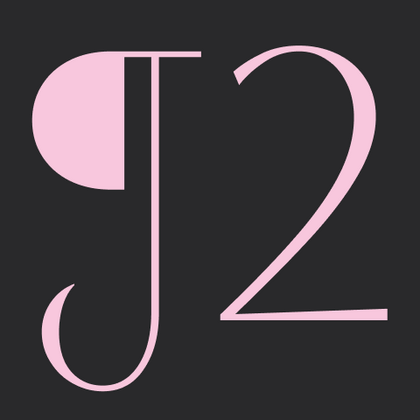
Нежные шрифты
Если требуются гарнитуры с деликатной эстетикой, где каждая линия передает легкость и изящество, отлично подойдут нежные шрифты. Их отличают плавные закругления, тонкие штрихи и воздушные пропорции, создающие ощущение тонкого вкуса. В коллекции TypeType представлены как каллиграфические варианты с рукописными нюансами, так и ультралегкие гротески — все они идеально подходят для свадебной полиграфии, косметического брендинга и женских изданий.
TT Odellia — старостильная антиква с современным рисунком, вдохновлённая венецианскими шрифтами и классической музыкой.
TT Rationalist — функциональный и оригинальный брусковый шрифт с актуальным рисунком. Он универсален и подходит как для заголовков, так и для массивов текста.
TT Jenevers стилистически относится к голландским антиквам нового стиля. В гарнитуре присутствуют характерные детали, свойственные голландским антиквам — это ассиметричная форма засечек или нерегулярный наклон овалов.
TT Quaris — изысканная и современная ленточная антиква. Перед разработкой этой гарнитуры мы провели глубокое исследование архетипов ленточных антикв.
TT Ricordi Allegria — современная ленточная антиква, отличительные особенности которой, гиперболизированная разноширинность в пропорциях, контраст между штрихами, клиновидные окончания штрихов и отсутствие традиционных засечек.
TT Modernoir — акцидентный гротеск с разноширинными пропорциями. Плавные линии и изящные формы ар-нуво в этом шрифте сочетаются с ритмичностью и импровизационной свободой джаза.
TT Ricordi Greto — неконтрастный флорентийский гротеск с динамичными пропорциями. Это единственный гротеск среди антикв в коллекции TT Ricordi, при этом в нем сохранились едва заметные засечки, отсылающие к прототипу.
TT Fellows — гуманистический гротеск с механистическими мотивами. Открытые формы, дружелюбно-нейтральный характер тонких весов и ещё более мягкий характер в жирных начертаниях.
TT Ramillas — стильная и современная антиква. Включает уникальные декоративные начертания и буквицы с цветочным орнаментом.
TT Paplane — акцидентный сквадраченный гротеск. Так, характерные черты этого гротеска — сквадраченные формы, 45-градусные срезы и обтекаемые внешние контуры.
TT Cometus — современная брусковая антиква. Название гарнитуры отсылает к образу кометы — мощного увесистого тела с красивым хвостом, грациозно рассекающего космические просторы с огромной скоростью.
TT Ricks — выразительная антиква с острым характером. Создавая ее, мы вдохновлялись шрифтом De Vinne, разработанным Густавом Шредером в 1892 году. Это «злая» антиква, которая, впрочем, иногда усмиряет свой дерзкий нрав.
TT Ricordi Marmo продолжает серию экспериментальных гарнитур, созданных в рамках проекта TT Ricordi. TT Ricordi Marmo создавался как плакатный шрифт, поэтому строчной набор в нем заменяет капитель.
Гарнитура TT Ricordi является коллекцией из трёх дисплейных заголовочных антикв, призванных значительно разнообразить традиционную шрифтовую палитру.
TT Hazelnuts — это акцидентная шрифтовая гарнитура без засечек с набором плавных и красивых декоративных элементов. Не смотря на свою геометрическую сущность, в данном шрифте чувствуется след человеческой руки, при желании можно взять перо и поворачивая его нарисовать практически весь шрифт.